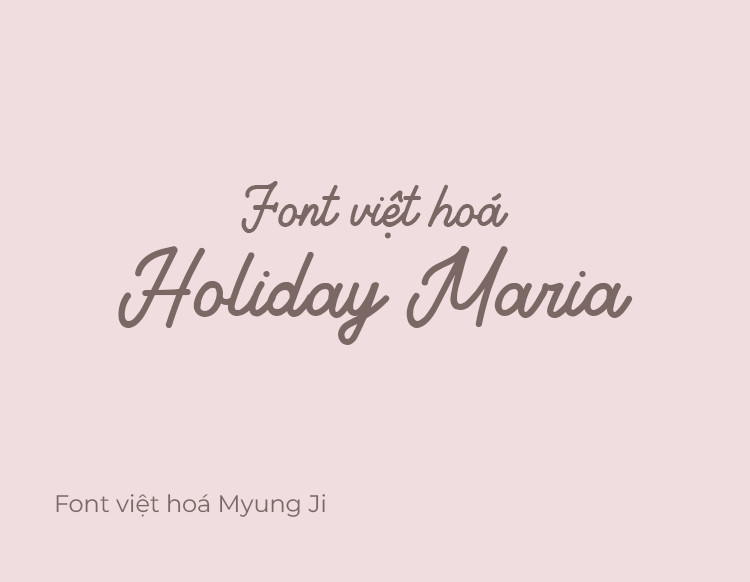
Giới thiệu về Font việt hoá MJ Holiday Maria Regular
Trong thế giới thiết kế đồ họa, việc lựa chọn một Font Chữ phù hợp đóng vai trò quyết định đến cảm xúc của người xem. Font việt hoá MJ Holiday Maria Regular là một bộ font mang phong cách script hiện đại, với những đường nét uyển chuyển và thanh lịch. Đây là lựa chọn lý tưởng cho những ai đang tìm kiếm sự kết hợp giữa nét vẽ tay tự nhiên và sự chỉn chu trong từng ký tự. Bộ font này đã được tối ưu hóa tiếng Việt hoàn chỉnh, giúp các nhà sáng tạo nội dung tại Việt Nam dễ dàng sử dụng mà không lo lỗi hiển thị.
Đặc điểm nổi bật của MJ Holiday Maria Regular
Đặc trưng của Font việt hoá MJ Holiday Maria Regular nằm ở các đường nét bay bổng nhưng vẫn đảm bảo tính dễ đọc. Font sở hữu bộ ký tự phong phú, bao gồm cả các ký tự thay thế đặc biệt, giúp người dùng tùy biến phong cách thiết kế theo ý muốn cá nhân. Với định dạng Regular cân đối, font chữ này không quá đậm cũng không quá mảnh, tạo nên sự hài hòa khi áp dụng vào nhiều bề mặt chất liệu khác nhau.
Ứng dụng của Font việt hoá MJ Holiday Maria Regular trong giáo dục và đời sống
Nhờ vẻ ngoài thân thiện, Font việt hoá MJ Holiday Maria Regular thường xuyên được các bạn học sinh và giáo viên tin dùng trong việc làm thiệp chúc mừng, bài thuyết trình hoặc trang trí sổ tay (bullet journal). Sự mềm mại của font giúp các thông điệp trở nên ấm áp và chân thành hơn.
Lưu ý khi sử dụng trong thiết kế chuyên nghiệp
Ngoài giáo dục, font chữ này còn xuất hiện phổ biến trong thiết kế logo, bao bì sản phẩm thủ công và các ấn phẩm quảng cáo sự kiện lễ hội. Bạn nên kết hợp nó với các font sans-serif tối giản để tạo ra sự tương phản bắt mắt và chuyên nghiệp hơn cho tác phẩm của mình.